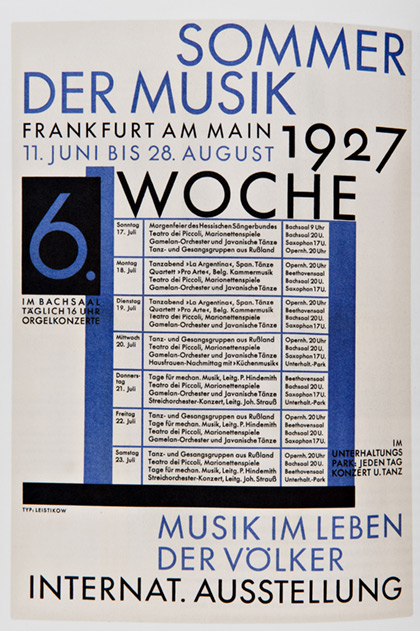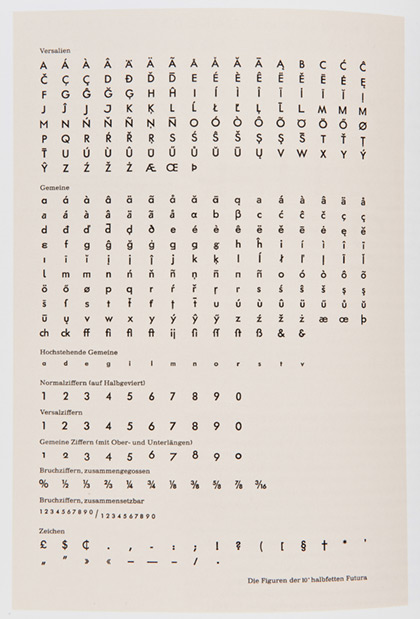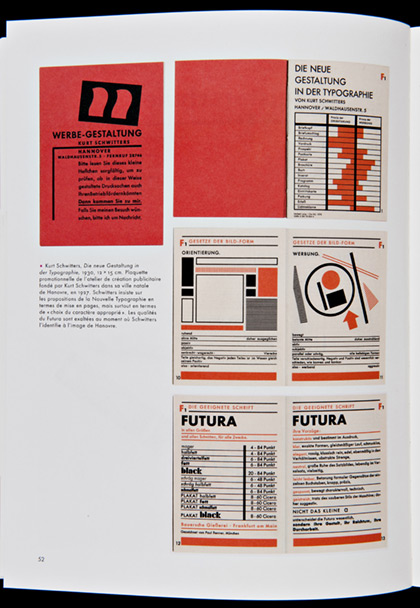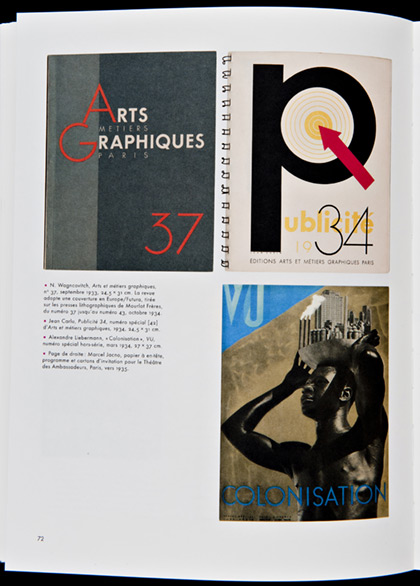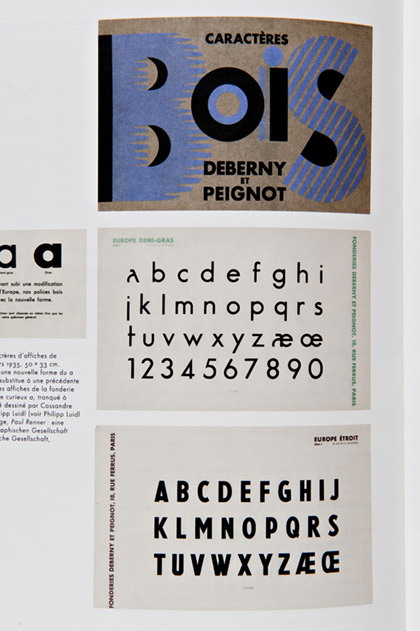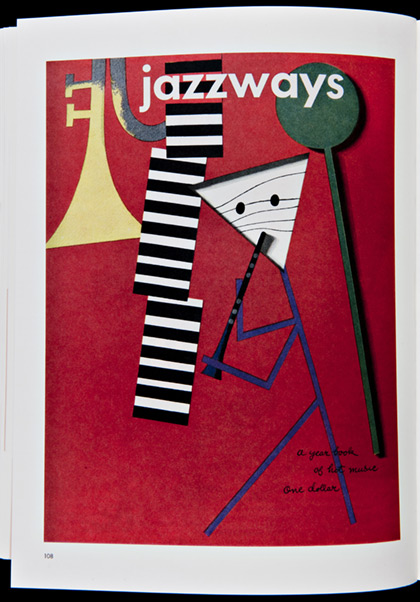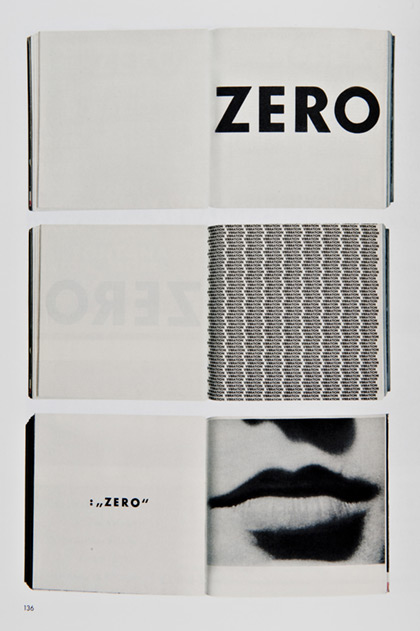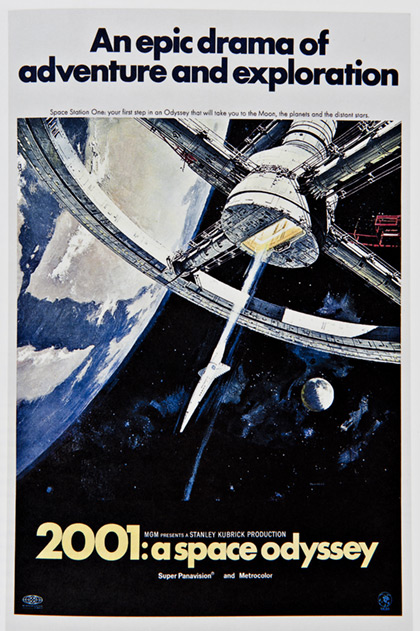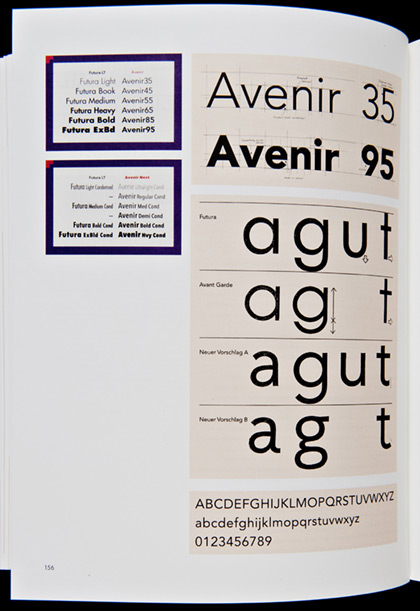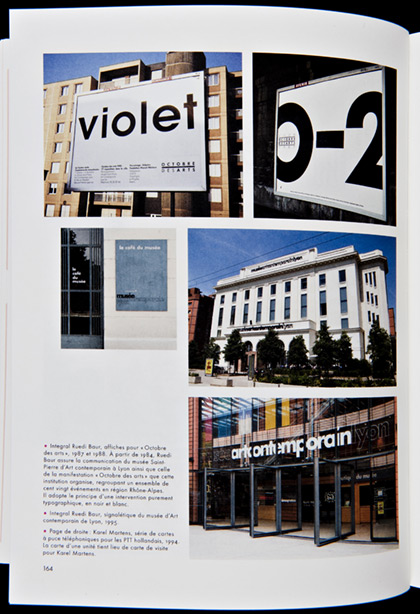
Le FUTURA | par Alexandre Dumas de Rauly & Michel Wlassikoff | histoire et analyse du caractère de Paul Renner
C’est avec une immense joie que je publie ce billet pour vous montrer ce magnifique ouvrage consacré à la création et à la vie du caractère FUTURA.
ISBN 978-2-9155-4239-4 vous pouvez, que dis-je vous devez vous le procurer, dans toutes les bonnes librairies d’Arts Graphiques ou bien chez Amazon. Écrit en collaboration par Alexandre Dumas de Rauly & Michel Wlassikoff, il parcourt en 9 chapîtres préfacé par Étienne Robial, la naissance logique de cette police, dessinée par Paul Renner sur la base d’un dessin d’Antique en raison de l’invention chez les phéniciens de ce type de tracé (700 av/JC). Il raconte par le menu comment ce dessin a conquis le monde entier partant du Bauhaus chassé par le régime nazi, parcourant les USA pour finalement nous revenir par le biais de la publicité qui y trouvait la simplicité et l’efficacité neutre pour vendre la Wolkswagen ou pour produire l’identité visuelle de Canal Plus.